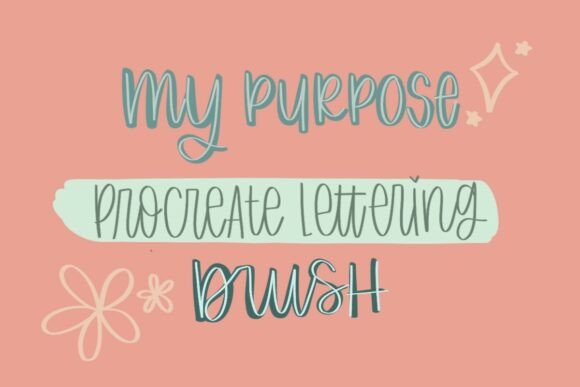
Procreate Lettering Brush My Purpose
Procreate Lettering Brush My Purpose – Revue détaillée
Vous cherchez le brush Procreate qui transformera vos créations de lettrage? Le My Purpose est la réponse. Conçu pour les artistes numériques exigeants, ce pinceau polyvalent offre une fluidité exceptionnelle et des détails précis qui donnent vie à chaque lettre.
- Polyvalence inégalée : idéal pour le hand‑lettering, les titres décoratifs, les citations inspirantes et même les petits ornements.
- Contrôle total : la pointe sensible à la pression vous permet de varier l’épaisseur des traits en un seul geste, pour un rendu naturel et organique.
- Détails raffinés : les micro‑textures intégrées ajoutent les finitions qui font toute la différence dans un projet professionnel.
En résumé, My Purpose n’est pas simplement un autre pinceau de lettrage ; c’est un véritable levier de créativité qui élève vos projets au niveau supérieur. Que vous soyez débutant ou professionnel, ce brush vous aidera à réaliser des compositions élégantes, précises et impactantes.
Boostez votre workflow, enrichissez vos designs et laissez votre style parler grâce à My Purpose – le brush Procreate incontournable pour tous vos besoins en lettrage.